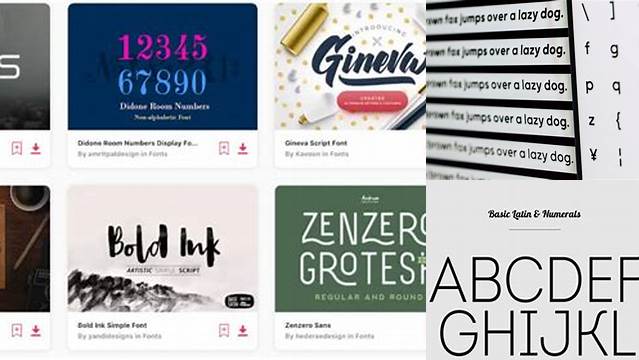
Font Gratis Terbaik: Unduh Sekarang!
Hey guys! Mencari jenis font gratis untuk proyek desain kamu? Pas banget! Di artikel ini, kita bakal ngebahas tuntas berbagai jenis font keren yang bisa kamu unduh tanpa bayar sepeser pun. Mulai dari yang klasik sampai yang modern, semua ada! Jadi, siap-siap mempercantik desain kamu dengan font-font kece ini ya!
1. Apa itu Font dan Mengapa Penting?
Sebelum kita terjun lebih dalam ke jenis font gratis, yuk kita pahami dulu apa itu font dan kenapa font itu penting banget dalam desain. Font, sederhananya, adalah gaya visual dari teks. Bayangin deh, kalau semua tulisan di dunia ini pakai font yang sama, pasti bosenin banget kan? Nah, font inilah yang memberikan karakter, gaya, dan kepribadian pada teks.
Dalam dunia desain, pemilihan font yang tepat bisa bikin perbedaan besar. Font bisa mempengaruhi bagaimana pesan kamu diterima oleh audiens. Misalnya, font yang elegan dan klasik cocok untuk desain yang formal dan mewah, sementara font yang playful dan quirky lebih pas untuk desain yang santai dan ceria. Jadi, jangan pernah meremehkan kekuatan sebuah font ya!
Font juga memegang peranan penting dalam branding. Sebuah merek bisa membangun identitas visual yang kuat dengan menggunakan font yang konsisten di semua materi promosinya. Coba deh perhatiin logo-logo merek terkenal, pasti masing-masing punya gaya font yang khas kan? Itulah kenapa pemilihan font adalah langkah krusial dalam membangun brand identity yang kuat dan mudah diingat.
Selain itu, font juga berperan penting dalam keterbacaan. Font yang mudah dibaca akan membuat teks lebih nyaman dibaca, sehingga pesan kamu bisa tersampaikan dengan baik. Sebaliknya, font yang terlalu rumit atau aneh justru bisa bikin pembaca pusing dan akhirnya malah mengabaikan pesan kamu. Jadi, pastikan kamu memilih font yang estetis sekaligus mudah dibaca ya!
2. Mengapa Memilih Font Gratis?
Nah, sekarang kita bahas kenapa sih kita harus memilih jenis font gratis? Jelas, alasan utamanya adalah karena gratis! Tapi, jangan salah, meskipun gratis, bukan berarti kualitasnya murahan ya. Sekarang ini, ada banyak banget desainer font yang baik hati membagikan karya mereka secara gratis. Jadi, kamu bisa mendapatkan font berkualitas tinggi tanpa harus mengeluarkan uang sepeser pun.
Selain itu, memilih font gratis juga bisa jadi pilihan yang cerdas buat kamu yang baru mulai belajar desain atau punya budget terbatas. Kamu bisa bereksperimen dengan berbagai jenis font tanpa khawatir kehabisan uang. Ini adalah kesempatan yang bagus untuk menemukan gaya font yang paling cocok dengan kepribadian dan proyek desain kamu.
Terakhir, dengan banyaknya pilihan jenis font gratis yang tersedia, kamu bisa lebih kreatif dan eksploratif dalam desain. Kamu bisa mencoba berbagai gaya font yang berbeda-beda, dari yang klasik sampai yang modern, tanpa ada batasan biaya. Ini bisa memicu ide-ide baru dan menghasilkan desain yang lebih unik dan menarik.
3. Perbedaan Font Serif dan Sans-Serif
Dalam dunia tipografi, ada dua kategori utama font, yaitu serif dan sans-serif. Perbedaan mendasar antara keduanya terletak pada adanya “serif” atau garis kecil yang menempel di ujung huruf. Font serif punya serif, sementara font sans-serif tidak punya.
Font serif seringkali dianggap lebih klasik dan formal. Garis-garis serif memberikan kesan elegan dan tradisional. Font serif biasanya digunakan untuk teks panjang, seperti di buku, majalah, atau koran, karena dianggap lebih mudah dibaca dalam jumlah banyak. Beberapa contoh font serif yang populer adalah Times New Roman, Garamond, dan Georgia.
Sebaliknya, font sans-serif punya tampilan yang lebih modern dan bersih. Tanpa serif, huruf-huruf terlihat lebih sederhana dan minimalis. Font sans-serif seringkali digunakan untuk judul, subjudul, atau teks pendek, karena memberikan kesan yang kuat dan tegas. Beberapa contoh font sans-serif yang populer adalah Arial, Helvetica, dan Open Sans.
Pemilihan antara font serif dan sans-serif tergantung pada gaya desain dan pesan yang ingin kamu sampaikan. Kalau kamu mau desain yang klasik dan elegan, font serif bisa jadi pilihan yang tepat. Tapi, kalau kamu mau desain yang modern dan minimalis, font sans-serif lebih cocok. Ada juga tren yang menggabungkan keduanya, misalnya menggunakan font serif untuk judul dan font sans-serif untuk isi teks.
4. Font Script: Elegan dan Personal
Selain serif dan sans-serif, ada juga kategori font yang disebut script. Font script meniru gaya tulisan tangan, sehingga memberikan kesan yang elegan, personal, dan artistik. Font script cocok digunakan untuk desain yang membutuhkan sentuhan manusiawi, seperti undangan pernikahan, kartu ucapan, atau logo merek yang ingin terlihat unik.
Ada berbagai jenis font script, mulai dari yang formal dan mewah, sampai yang kasual dan playful. Font script kaligrafi, misalnya, punya garis-garis yang indah dan anggun, cocok untuk desain yang formal. Sementara font script kuas punya tekstur yang lebih kasar dan spontan, cocok untuk desain yang lebih santai dan kreatif.
Penggunaan font script harus hati-hati, karena tidak semua font script mudah dibaca. Font script yang terlalu rumit atau kecil bisa bikin teks sulit dibaca, terutama dalam jumlah banyak. Jadi, pastikan kamu memilih font script yang jelas dan proporsional. Selain itu, font script sebaiknya digunakan sebagai aksen saja, bukan untuk seluruh teks.
5. Font Display: Unik dan Mencolok
Kategori font display mencakup jenis font yang unik, mencolok, dan punya karakter yang kuat. Font display biasanya digunakan untuk judul, logo, atau poster, karena tujuannya adalah untuk menarik perhatian. Font display bisa punya berbagai gaya, mulai dari yang retro, vintage, sampai yang futuristik.
Font display seringkali punya bentuk huruf yang tidak biasa, detail yang rumit, atau tekstur yang unik. Beberapa font display bahkan punya ilustrasi atau ornamen yang terintegrasi dalam huruf. Ini membuat font display jadi pilihan yang tepat untuk desain yang ingin tampil beda dan memorable.
Sama seperti font script, penggunaan font display juga harus hati-hati. Font display yang terlalu berlebihan bisa bikin desain terlihat norak atau sulit dibaca. Jadi, pastikan kamu memilih font display yang sesuai dengan gaya desain dan pesan yang ingin kamu sampaikan. Font display sebaiknya digunakan secukupnya saja, sebagai elemen yang menonjol.
6. Font Monospace: Klasik dan Teknis
Font monospace adalah jenis font yang punya lebar karakter yang sama. Artinya, setiap huruf, angka, dan simbol punya lebar yang sama, tidak peduli bentuknya. Font monospace seringkali digunakan dalam pemrograman, coding, atau penulisan kode, karena memudahkan pembacaan dan penataan kode.
Font monospace juga punya daya tarik klasik dan teknis. Font monospace seringkali dikaitkan dengan mesin tik atau komputer zaman dulu. Ini memberikan kesan yang retro dan unik. Beberapa font monospace bahkan punya tampilan yang futuristik atau industrial.
Font monospace bisa digunakan untuk berbagai tujuan desain, mulai dari logo, poster, sampai website. Font monospace bisa memberikan kesan yang kuat, tegas, dan profesional. Tapi, font monospace sebaiknya tidak digunakan untuk teks panjang, karena bisa bikin pembaca cepat lelah.
7. Situs Web untuk Mengunduh Font Gratis
Nah, sekarang kita bahas di mana kamu bisa menemukan jenis font gratis yang berkualitas. Ada banyak banget situs web yang menawarkan font gratis, tapi tidak semuanya aman dan terpercaya. Berikut ini beberapa situs web yang bisa kamu andalkan untuk mengunduh font gratis:
- Google Fonts: Google Fonts adalah salah satu sumber font gratis terbesar dan terpopuler di dunia. Google Fonts menawarkan ribuan font dengan berbagai gaya dan bahasa. Semua font di Google Fonts bersifat open source, yang berarti kamu bisa menggunakannya untuk keperluan komersial maupun non-komersial.
- DaFont: DaFont adalah situs web yang sudah lama berkecimpung di dunia font gratis. DaFont punya koleksi font yang sangat beragam, mulai dari yang klasik sampai yang unik dan aneh. Tapi, kamu harus hati-hati saat mengunduh font dari DaFont, karena beberapa font mungkin punya lisensi yang berbeda.
- Font Squirrel: Font Squirrel adalah situs web yang fokus pada font gratis untuk keperluan komersial. Semua font di Font Squirrel punya lisensi yang jelas dan aman untuk digunakan dalam proyek komersial. Font Squirrel juga punya fitur Font Identifier yang bisa membantu kamu mengidentifikasi font yang kamu lihat di gambar.
- Creative Market Free Goods: Creative Market adalah marketplace untuk berbagai aset desain, termasuk font. Setiap minggu, Creative Market menawarkan beberapa aset gratis, termasuk font gratis. Kamu bisa mendapatkan font premium secara gratis dengan memanfaatkan penawaran ini.
- MyFonts: MyFonts adalah marketplace font yang besar dan terpercaya. MyFonts punya koleksi font yang sangat lengkap, termasuk font gratis. Kamu bisa mencari font gratis di MyFonts dengan memfilter berdasarkan harga.
8. Lisensi Font: Pahami Sebelum Menggunakan
Sebelum kamu menggunakan jenis font gratis yang sudah kamu unduh, penting untuk memahami lisensi font. Lisensi font adalah perjanjian hukum antara pembuat font dan pengguna font. Lisensi font menentukan bagaimana kamu boleh menggunakan font tersebut.
Ada berbagai jenis lisensi font, mulai dari yang sangat permisif sampai yang sangat restriktif. Beberapa font gratis punya lisensi open source, yang berarti kamu bisa menggunakannya untuk keperluan apa pun, termasuk komersial, tanpa batasan. Tapi, ada juga font gratis yang hanya boleh digunakan untuk keperluan non-komersial.
Beberapa istilah yang sering muncul dalam lisensi font antara lain:
- Commercial use: Penggunaan font untuk keperluan komersial, seperti desain logo, iklan, atau produk yang dijual.
- Non-commercial use: Penggunaan font untuk keperluan non-komersial, seperti desain pribadi, blog, atau proyek amal.
- Embedding: Penanaman font dalam dokumen atau aplikasi, sehingga font tersebut bisa ditampilkan meskipun pengguna tidak punya font tersebut di komputernya.
- Modification: Modifikasi font, seperti mengubah bentuk huruf atau menambahkan elemen baru.
- Redistribution: Pendistribusian font, seperti membagikan font tersebut ke orang lain.
Pastikan kamu membaca dan memahami lisensi font sebelum menggunakannya. Jika kamu tidak yakin, sebaiknya hubungi pembuat font untuk meminta klarifikasi. Melanggar lisensi font bisa berakibat hukum.
9. Cara Memasang Font di Komputer
Setelah kamu mengunduh jenis font gratis yang kamu inginkan, langkah selanjutnya adalah memasang font tersebut di komputer kamu. Cara memasang font berbeda-beda tergantung pada sistem operasi yang kamu gunakan. Berikut ini cara memasang font di Windows dan macOS:
Windows:
- Ekstrak file font dari file ZIP (jika ada).
- Klik kanan pada file font (biasanya berekstensi .ttf atau .otf).
- Pilih “Install”.
- Font akan terpasang secara otomatis dan bisa langsung digunakan di aplikasi kamu.
macOS:
- Ekstrak file font dari file ZIP (jika ada).
- Buka aplikasi Font Book (bisa dicari di Spotlight).
- Drag dan drop file font ke jendela Font Book.
- Font akan terpasang secara otomatis dan bisa langsung digunakan di aplikasi kamu.
10. Menggunakan Font di Aplikasi Desain
Setelah font terpasang di komputer kamu, kamu bisa langsung menggunakannya di aplikasi desain favorit kamu, seperti Adobe Photoshop, Adobe Illustrator, Canva, atau Figma. Cara menggunakan font di aplikasi desain biasanya sama:
- Buka aplikasi desain kamu.
- Buat dokumen atau proyek baru.
- Pilih tool teks.
- Klik dan drag untuk membuat kotak teks.
- Ketik teks yang kamu inginkan.
- Pilih teks yang sudah kamu ketik.
- Buka menu font.
- Cari dan pilih font yang sudah kamu pasang.
- Teks kamu akan berubah menggunakan font yang kamu pilih.
11. Kombinasi Font: Menciptakan Harmoni Visual
Dalam desain, menggabungkan beberapa jenis font bisa menciptakan harmoni visual yang menarik. Tapi, menggabungkan font juga tidak boleh sembarangan. Ada beberapa prinsip yang perlu kamu perhatikan agar kombinasi font kamu terlihat bagus dan profesional.
Salah satu prinsip dasar dalam kombinasi font adalah kontras. Kamu bisa menggabungkan font serif dengan font sans-serif, atau font yang tebal dengan font yang tipis. Kontras akan membuat masing-masing font terlihat lebih menonjol dan menarik.
Selain kontras, kamu juga perlu memperhatikan hierarki. Font yang kamu gunakan untuk judul harus lebih menonjol daripada font yang kamu gunakan untuk isi teks. Kamu bisa menggunakan ukuran, ketebalan, atau gaya font yang berbeda untuk menciptakan hierarki.
Konsistensi juga penting dalam kombinasi font. Sebaiknya kamu tidak menggunakan terlalu banyak font dalam satu desain. Cukup gunakan 2-3 font saja, dan pastikan font-font tersebut punya gaya yang serasi.
12. Tips Memilih Font yang Tepat
Pemilihan font yang tepat adalah kunci untuk menciptakan desain yang efektif. Berikut ini beberapa tips yang bisa kamu ikuti saat memilih font:
- Pertimbangkan pesan dan target audiens: Font yang kamu pilih harus sesuai dengan pesan yang ingin kamu sampaikan dan target audiens kamu. Font yang formal cocok untuk audiens yang profesional, sementara font yang playful cocok untuk audiens yang lebih muda.
- Perhatikan keterbacaan: Font yang bagus adalah font yang mudah dibaca. Hindari font yang terlalu rumit atau kecil, terutama untuk teks panjang.
- Sesuaikan dengan gaya desain: Font yang kamu pilih harus sesuai dengan gaya desain kamu secara keseluruhan. Font yang modern cocok untuk desain yang minimalis, sementara font yang vintage cocok untuk desain yang retro.
- Eksperimen dan eksplorasi: Jangan takut untuk mencoba berbagai jenis font yang berbeda-beda. Eksperimen dan eksplorasi bisa membantu kamu menemukan font yang paling cocok untuk proyek kamu.
13. Tren Font Terkini
Dunia tipografi terus berkembang, dan tren font juga terus berubah. Mengikuti tren font bisa membantu kamu menciptakan desain yang up-to-date dan relevan. Berikut ini beberapa tren font terkini yang perlu kamu ketahui:
- Font serif modern: Font serif tidak lagi hanya untuk desain yang klasik. Sekarang, ada banyak font serif modern yang punya tampilan yang segar dan unik.
- Font sans-serif geometris: Font sans-serif geometris punya bentuk huruf yang sederhana dan presisi. Font ini cocok untuk desain yang minimalis dan futuristik.
- Font display tebal: Font display tebal punya karakter yang kuat dan mencolok. Font ini cocok untuk judul, logo, atau poster.
- Font script kasual: Font script kasual punya tampilan yang lebih santai dan manusiawi. Font ini cocok untuk desain yang personal dan kreatif.
- Font variabel: Font variabel adalah jenis font yang bisa diubah-ubah parameternya, seperti ketebalan, lebar, atau kemiringan. Font ini memberikan fleksibilitas yang tinggi dalam desain.
14. Font untuk Logo: Membangun Identitas Merek
Font memegang peranan penting dalam desain logo. Font yang tepat bisa membantu membangun identitas merek yang kuat dan mudah diingat. Saat memilih font untuk logo, ada beberapa hal yang perlu kamu pertimbangkan:
- Kepribadian merek: Font yang kamu pilih harus mencerminkan kepribadian merek kamu. Font yang elegan cocok untuk merek yang mewah, sementara font yang playful cocok untuk merek yang ceria.
- Keterbacaan: Logo harus mudah dibaca, bahkan dalam ukuran kecil. Hindari font yang terlalu rumit atau tipis.
- Keunikan: Logo harus unik dan mudah dibedakan dari logo merek lain. Pilih font yang tidak terlalu umum atau pasaran.
- Versatilitas: Logo harus terlihat bagus dalam berbagai media, mulai dari website, kartu nama, sampai merchandise. Pilih font yang fleksibel dan bisa diadaptasi.
15. Font untuk Website: Meningkatkan Pengalaman Pengguna
Font juga penting dalam desain website. Font yang tepat bisa meningkatkan keterbacaan, navigasi, dan pengalaman pengguna secara keseluruhan. Saat memilih font untuk website, ada beberapa hal yang perlu kamu perhatikan:
- Keterbacaan: Website harus mudah dibaca di berbagai perangkat, mulai dari komputer, tablet, sampai smartphone. Pilih font yang jelas dan proporsional.
- Hierarki: Website harus punya hierarki visual yang jelas. Gunakan font yang berbeda untuk judul, subjudul, dan isi teks.
- Konsistensi: Website harus punya gaya font yang konsisten di seluruh halaman. Ini akan menciptakan tampilan yang profesional dan terpadu.
- Kecepatan: Font bisa mempengaruhi kecepatan loading website. Pilih font yang ringan dan dioptimalkan untuk web.
16. Font untuk Media Sosial: Menarik Perhatian Online
Media sosial adalah platform yang visual. Font yang menarik bisa membantu kamu menarik perhatian pengguna dan menyampaikan pesan kamu dengan efektif. Saat memilih font untuk media sosial, ada beberapa hal yang perlu kamu pertimbangkan:
- Visibilitas: Font harus terlihat jelas di berbagai ukuran layar, terutama di smartphone.
- Kontras: Font harus kontras dengan latar belakang agar mudah dibaca.
- Kepribadian: Font harus sesuai dengan kepribadian merek kamu.
- Tren: Mengikuti tren font terkini bisa membuat konten media sosial kamu terlihat lebih segar dan relevan.
17. Font untuk Desain Cetak: Kualitas yang Optimal
Desain cetak punya требования yang berbeda dengan desain digital. Font yang kamu gunakan untuk desain cetak harus punya kualitas yang optimal agar hasilnya terlihat bagus dan profesional. Saat memilih font untuk desain cetak, ada beberapa hal yang perlu kamu perhatikan:
- Resolusi: Font harus punya resolusi yang tinggi agar tidak terlihat pecah atau buram saat dicetak.
- Ketebalan: Font harus punya ketebalan yang cukup agar mudah dibaca saat dicetak.
- Spasi: Font harus punya spasi yang tepat agar tidak terlalu rapat atau terlalu renggang.
- Proofing: Selalu lakukan proofing atau uji cetak sebelum mencetak desain akhir. Ini akan membantu kamu memastikan font terlihat bagus dan sesuai dengan harapan.
18. Font dan Branding: Membangun Citra Merek
Seperti yang sudah kita bahas sebelumnya, font memegang peranan penting dalam branding. Font yang tepat bisa membantu membangun citra merek yang kuat, konsisten, dan mudah diingat. Saat memilih font untuk branding, ada beberapa hal yang perlu kamu pertimbangkan:
- Kepribadian merek: Font harus mencerminkan kepribadian merek kamu. Apakah merek kamu elegan, ceria, atau profesional?
- Target audiens: Font harus menarik bagi target audiens kamu. Apa preferensi gaya mereka?
- Pesaing: Font harus membedakan merek kamu dari pesaing. Apa yang membuat merek kamu unik?
- Konsistensi: Font harus digunakan secara konsisten di semua materi branding, mulai dari logo, website, sampai media sosial.
19. Font dan Psikologi: Mempengaruhi Emosi
Tahukah kamu bahwa font bisa mempengaruhi emosi? Ya, jenis font yang berbeda bisa membangkitkan perasaan yang berbeda pula. Misalnya, font serif seringkali dikaitkan dengan kesan formal, klasik, dan terpercaya. Sementara font sans-serif seringkali dikaitkan dengan kesan modern, bersih, dan efisien.
Font script bisa membangkitkan perasaan elegan, personal, dan artistik. Sementara font display bisa membangkitkan perasaan unik, mencolok, dan kreatif. Dengan memahami psikologi font, kamu bisa memilih font yang tepat untuk menyampaikan pesan emosional yang kamu inginkan.
20. Font dan Keterbacaan: Prioritaskan Kenyamanan
Keterbacaan adalah faktor yang paling penting dalam pemilihan font. Font yang bagus adalah font yang mudah dibaca, nyaman di mata, dan tidak membuat pembaca cepat lelah. Keterbacaan penting untuk semua jenis desain, mulai dari website, buku, sampai poster.
Ada beberapa faktor yang mempengaruhi keterbacaan font, antara lain:
- Ukuran: Ukuran font harus cukup besar agar mudah dibaca.
- Ketebalan: Ketebalan font harus sesuai agar tidak terlalu tipis atau terlalu tebal.
- Kontras: Font harus kontras dengan latar belakang agar mudah dibaca.
- Spasi: Spasi antar huruf dan baris harus tepat agar tidak terlalu rapat atau terlalu renggang.
- Gaya: Gaya font harus sesuai dengan tujuan desain dan target audiens.
21. Font dan Aksesibilitas: Desain untuk Semua
Dalam desain, aksesibilitas adalah hal yang penting untuk dipertimbangkan. Aksesibilitas berarti desain kamu bisa digunakan oleh semua orang, termasuk orang dengan disabilitas. Saat memilih font, ada beberapa hal yang perlu kamu perhatikan agar desain kamu lebih aksesibel:
- Kontras: Gunakan font yang kontras dengan latar belakang agar mudah dibaca oleh orang dengan gangguan penglihatan.
- Ukuran: Gunakan ukuran font yang cukup besar agar mudah dibaca oleh orang dengan gangguan penglihatan.
- Gaya: Hindari font yang terlalu rumit atau dekoratif, karena bisa sulit dibaca oleh orang dengan disleksia.
- Alternatif: Sediakan alternatif teks untuk gambar atau ikon yang menggunakan font unik.
22. Font dan Bahasa: Mendukung Berbagai Karakter
Jika kamu mendesain untuk audiens internasional, kamu perlu memastikan font kamu mendukung berbagai bahasa dan karakter. Beberapa font hanya mendukung karakter Latin, sementara font lain mendukung karakter non-Latin, seperti Cyrillic, Greek, atau CJK (Chinese, Japanese, Korean).
Saat memilih font, pastikan font tersebut mendukung bahasa yang kamu butuhkan. Kamu bisa melihat daftar karakter yang didukung oleh font di situs web atau aplikasi desain kamu.
23. Font dan Open Source: Kolaborasi Kreatif
Font open source adalah jenis font yang lisensinya memungkinkan siapa saja untuk menggunakan, memodifikasi, dan mendistribusikan font tersebut secara gratis. Font open source adalah hasil kolaborasi kreatif dari berbagai desainer font di seluruh dunia.
Google Fonts adalah contoh platform yang menyediakan banyak font open source berkualitas tinggi. Dengan menggunakan font open source, kamu bisa mendukung kolaborasi kreatif dan berkontribusi pada komunitas desain.
24. Font dan Web Hosting: Optimasi Kinerja
Jika kamu menggunakan font khusus di website kamu, kamu perlu menghosting font tersebut di server kamu atau menggunakan layanan web font. Menghosting font sendiri bisa memberikan kontrol yang lebih besar, tapi juga bisa mempengaruhi kinerja website kamu.
Menggunakan layanan web font, seperti Google Fonts atau Adobe Fonts, bisa membantu mengoptimalkan kinerja website kamu. Layanan web font biasanya menggunakan CDN (Content Delivery Network) untuk mengirimkan font ke pengguna dengan cepat dan efisien.
25. Font dan SEO: Meningkatkan Peringkat Website
Font yang kamu gunakan di website kamu juga bisa mempengaruhi SEO (Search Engine Optimization). Google merekomendasikan untuk menggunakan font yang mudah dibaca dan dioptimalkan untuk web. Font yang mudah dibaca akan membuat pengunjung betah di website kamu, yang bisa meningkatkan peringkat website kamu di hasil pencarian.
Selain itu, Google juga merekomendasikan untuk menggunakan font yang dihosting di server yang cepat. Menggunakan layanan web font bisa membantu meningkatkan kecepatan loading website kamu, yang juga bisa mempengaruhi SEO.
26. Font dan Desain UI/UX: Pengalaman Pengguna yang Baik
Font memegang peranan penting dalam desain UI/UX (User Interface/User Experience). Font yang tepat bisa meningkatkan keterbacaan, navigasi, dan pengalaman pengguna secara keseluruhan. Saat memilih font untuk desain UI/UX, ada beberapa hal yang perlu kamu perhatikan:
- Keterbacaan: Font harus mudah dibaca di berbagai ukuran layar dan resolusi.
- Hierarki: Gunakan font yang berbeda untuk judul, subjudul, dan isi teks untuk menciptakan hierarki visual.
- Konsistensi: Gunakan gaya font yang konsisten di seluruh aplikasi atau website.
- Aksesibilitas: Pastikan font kamu mudah dibaca oleh semua pengguna, termasuk orang dengan disabilitas.
27. Font dan Legalitas: Hindari Pelanggaran Hak Cipta
Seperti yang sudah kita bahas sebelumnya, penting untuk memahami lisensi font sebelum menggunakannya. Menggunakan font tanpa izin atau melanggar lisensi font bisa berakibat hukum. Pastikan kamu selalu menggunakan font yang legal dan sesuai dengan ketentuan lisensi.
Jika kamu tidak yakin tentang lisensi font, sebaiknya hubungi pembuat font atau gunakan font open source yang lisensinya jelas dan permisif.
28. Font dan Update: Tetap Up-to-Date
Dunia tipografi terus berkembang, dan desainer font terus menciptakan font-font baru yang inovatif. Untuk tetap up-to-date, kamu perlu mengikuti tren font terkini dan mencoba font-font baru. Kamu bisa mengikuti blog desain, majalah desain, atau media sosial desainer font untuk mendapatkan informasi terbaru tentang font.
Selain itu, kamu juga perlu memperbarui font kamu secara berkala. Beberapa font mungkin memiliki update atau perbaikan bug yang bisa meningkatkan kualitas dan performa font.
29. Font dan Inspirasi: Mencari Ide Kreatif
Mencari inspirasi font bisa membantu kamu menemukan ide-ide kreatif untuk desain kamu. Ada banyak sumber inspirasi font, mulai dari buku, majalah, website, sampai lingkungan sekitar kamu. Kamu bisa mengamati font yang digunakan dalam logo, poster, atau signage di jalan.
Selain itu, kamu juga bisa mengunjungi museum tipografi atau pameran font untuk melihat berbagai jenis font dari berbagai era. Dengan mencari inspirasi font, kamu bisa mengembangkan selera tipografi kamu dan menemukan gaya font yang unik dan menarik.
30. Kesimpulan: Font Gratis untuk Desain yang Lebih Baik
Nah, guys, itulah pembahasan lengkap tentang jenis font gratis. Semoga artikel ini bermanfaat dan bisa membantu kamu menemukan font yang tepat untuk proyek desain kamu. Ingat, font adalah elemen penting dalam desain. Pemilihan font yang tepat bisa membuat desain kamu terlihat lebih profesional, menarik, dan efektif. Jadi, jangan ragu untuk bereksperimen dan eksplorasi dengan berbagai jenis font yang berbeda-beda. Selamat mendesain!